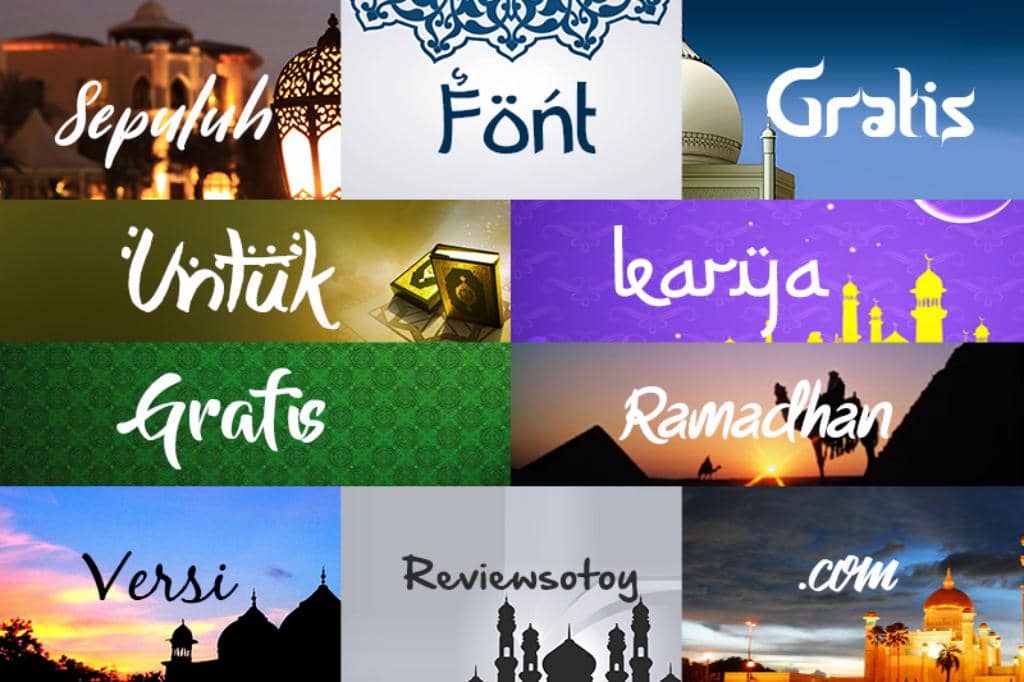
Font Ramadhan – Layaknya bulan-bulan penting lain pada umumnya, seperti Natal, Tahun Baru ataupun Imlek, Bulan Ramadan dan Lebaran juga mempunyai kekhasan tersendiri dalam perihal kreasi terutama ketika dalam perihal pemilihan font-nya. Memang kalian bisa saja sih memakai font lain untuk kreasi nan sedang kalian kerjakan. Tetapi rasanya menjadi kurang eye catching dan nggak tepat saja kalau font yang dipakai bukan nan unik dipakai ketika Ramadan atau Lebaran tiba.
12 Font Ramadhan Untuk Desain Bertema Lebaran
Nah, bagi kalian yang mau membuat desain sesuatu, mungkin kartu ucapan, poster, brosur, flyer ataupun untuk perihal lainnya, berikut ini ialah beberapa rekomendasi font ramadhan yang patut kalian coba gunakan.
1. Awal Ramadhan Font
Font satu ini berstatus freeware nama lain bebas digunakan ini mempunyai bentuk nan mirip huruf-huruf Hijaiyah. Dengan menggunakan font seperti ini, maka desainmu bakal menyiratkan nuansa Islami. Hanya saja, font ini mungkin bakal cocok hanya untuk digunakan sebagai titel atau sub-judul saja, bukan untuk isi content-nya lantaran sulur-sulur nan terdapat dalam font tersebut bakal membikin tulisan menjadi terasa penuh.
2. Special Ramadhan Font
Sama seperti font berjudul Awal Ramadhan, font dengan nama Special Ramadhan nan diciptakan oleh Nurfdesigns ini juga mempunyai kreasi mirip huruf-huruf Hijaiyah. Hanya saja perbedaannya dengan Awal Ramadhan ialah Special Ramadhan ini lebih bold dan blocking. Jadi amat cocok digunakan sebagai judul, sub-judul atau lainnya selain isi content. Walaupun bisa kalian unduh secara gratis, tapi Special Ramadhan ini berstatus personal use only alias tak diperkenankan untuk tujuan komersial.
3. Albarokah Font
Jika kalian pernah memandang bentuk kreasi kaligrafi Arab dengan ujung nan condong lancip, kalian juga bias membikin kreasi menggunakan font seperti itu, ialah memakai Albarokah nan diciptakan oleh NeutroneLabs.
Bentuk desain font Albarokah ini amat mirip dengan kreasi kaligrafi popular pada umumnya. Dan tetap seperti 2 font di atas, Albarakah tepat jika digunakan untuk titel dan sub-judul saja, lantaran kurang begitu tepat dipakai untuk tulisan utama. Font satu ini juga berstatus personal use only. Adapun jika kalian mau menggunakannya sebagai sarana promosi atau penggunaan komersial, maka wajib meminta izin terlebih dulu ke NeutroneLabs.
4. Puasa Ramadhan Font
Apabila kalian mau mencari dan menggunakan font Islami nan bisa digunakan bagus untuk judul, sub-judul ataupun isi tulisan di desain, maka font dengan titel Puasa Ramadhan nan diciptakan oleh Mozatype Studio ini ialah pilihan nan tepat.
Desain dari font satu ini cukup clean. Tidak banyak sulur atau tambahan ornamen lain dalam fontnya, jadi kalian bebas menggunakannya di posisi apapun.
Puasa Ramadhan ini berstatus personal use only dan uniknya, Mozatype Studio tak memberikan izin ataupun lisensi dalam bentuk apa saja agar font ini bisa digunakan untuk tujuan komersil. Jadi betul-betul hanya untuk penggunaan pribadi saja.
5. Brekshire Swash Font
Font berjudul Brekshire Swash nan diciptakan oleh Astigmatic One Eye Typographic Institute ini juga bisa kalian pakai. Baik untuk judul, sub-judul ataupun bagian inti desain. Bentuk fontnya memang tak terlalu menunjukkan style ke-Arab-an atau nan bertemakan Islami. Akan tetapi tetap cukup cocok untuk digunakan di dalam desain.
Satu perihal nan menarik ialah Brekshire Swash ini bisa kalian gunakan untuk penggunaan pribadi. Misal untuk tujuan komersial tanpa wajib meminta izin kepada sang pembuat dan pemilik font. Namun tetap aja, lisensinya tetap dimiliki oleh Astigmatic One Eye Typographic Institute.
6. Miracle Ramadhan
Miracle Ramadhan karya alpapranastudio.com adalah font bergaya arab yang memukau dengan nuansa otentik dan kasual. Ini akan sangat cocok digunakan untuk Branding, Desain Logo, Huruf, Jenis Logo, Pakaian, Poster, majalah, kemasan, poster, tas belanja, t-shirt, sampul buku, fotografi, acara khusus dan proyek desain lainnya.
7. Mozaik Ramadhan
Mozaik Ramadhan karya maknastudio.com ini adalah font tampilan yang modern, menyenangkan, dan unik, dipengaruhi oleh gaya Arab. Ini ditentukan oleh kurva halus dan sangat cocok untuk branding fashion atau desain editorial. Tambahkan dengan percaya diri ke proyek Anda, dan Anda akan menyukai hasilnya.
8. Sketsa Ramadhan
Sketsa Ramadhan adalah font Arab berkualitas tinggi yang dirancang oleh Hendra Pratama dan tersedia untuk diunduh gratis dan penggunaan pribadi. Versi gratis menyediakan semua huruf besar dan kecil dan beberapa karakter khusus juga.
12. Nestapha Font
Nestapha Ramadhan Arabic Font, kaligrafi, Religi, Muslim, canva, procreate, cricut. Font Modern dengan Gaya Elegan sangat cocok untuk branding, logo, undangan, poster, dan banyak lagi.